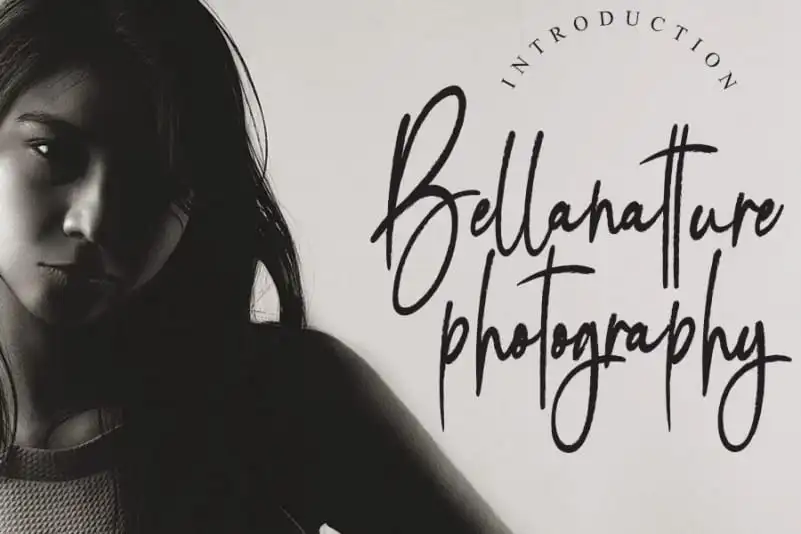
Bellanatture Script Font – Download Grátis
A Bellanatture Script Font é uma fonte de escrita manuscrita única que oferece um toque definitivamente pessoal ao seu projeto design. Seu estilo versátil faz dele a escolha perfeita para qualquer projeto que exija uma mão-direita, seja ele um convite matrimonial cheio de personalidade ou artesanato de papel elegante, até mesmo postagens sociais que destacam sua arte visual. Adentre a essência da autenticidade e beleza natural desta fonte em seu próximo design, ela é perfeita para criar mensagens memoráveis e incrivelmente belas.